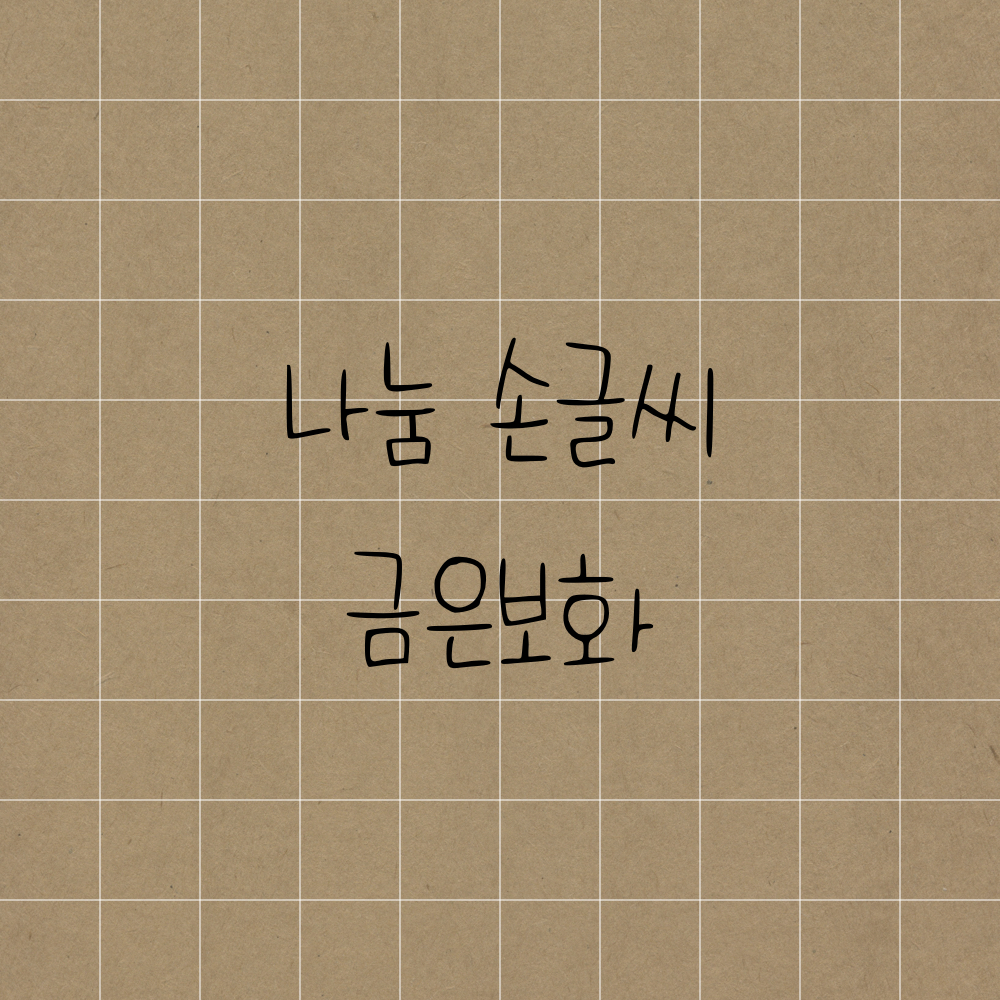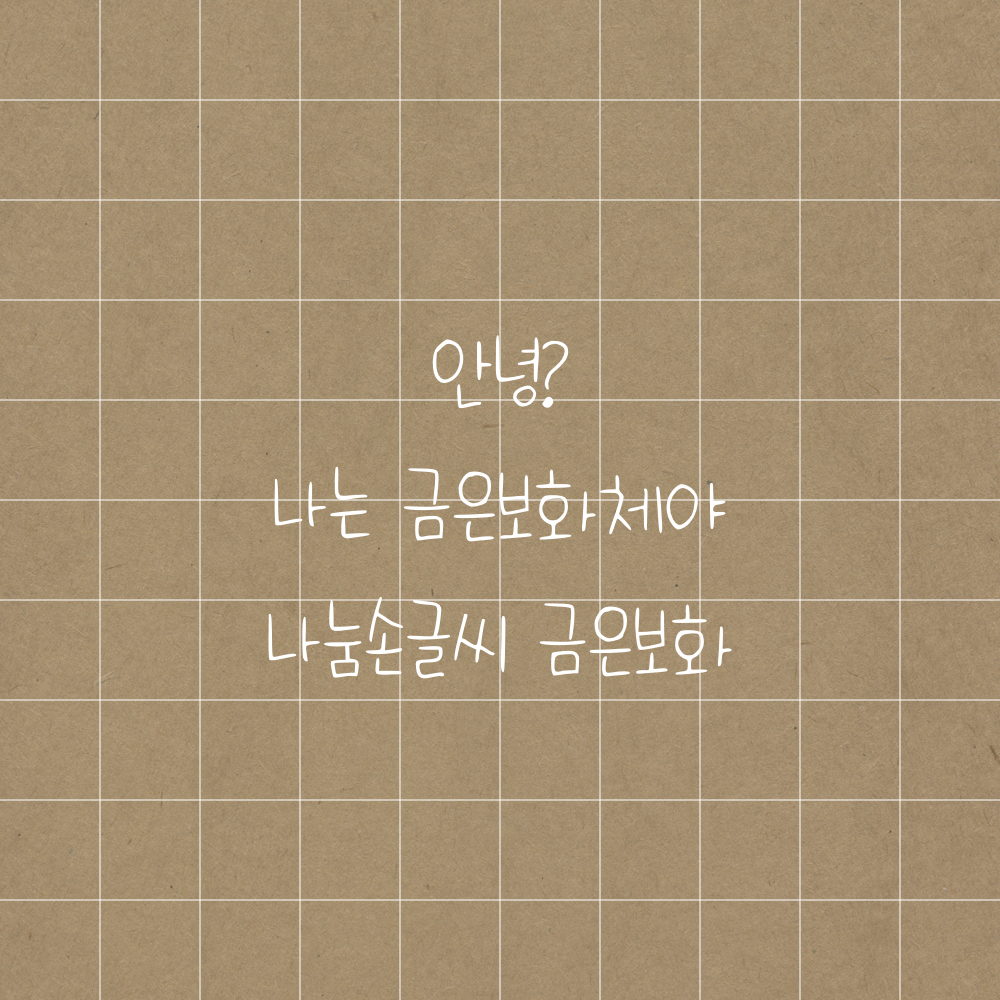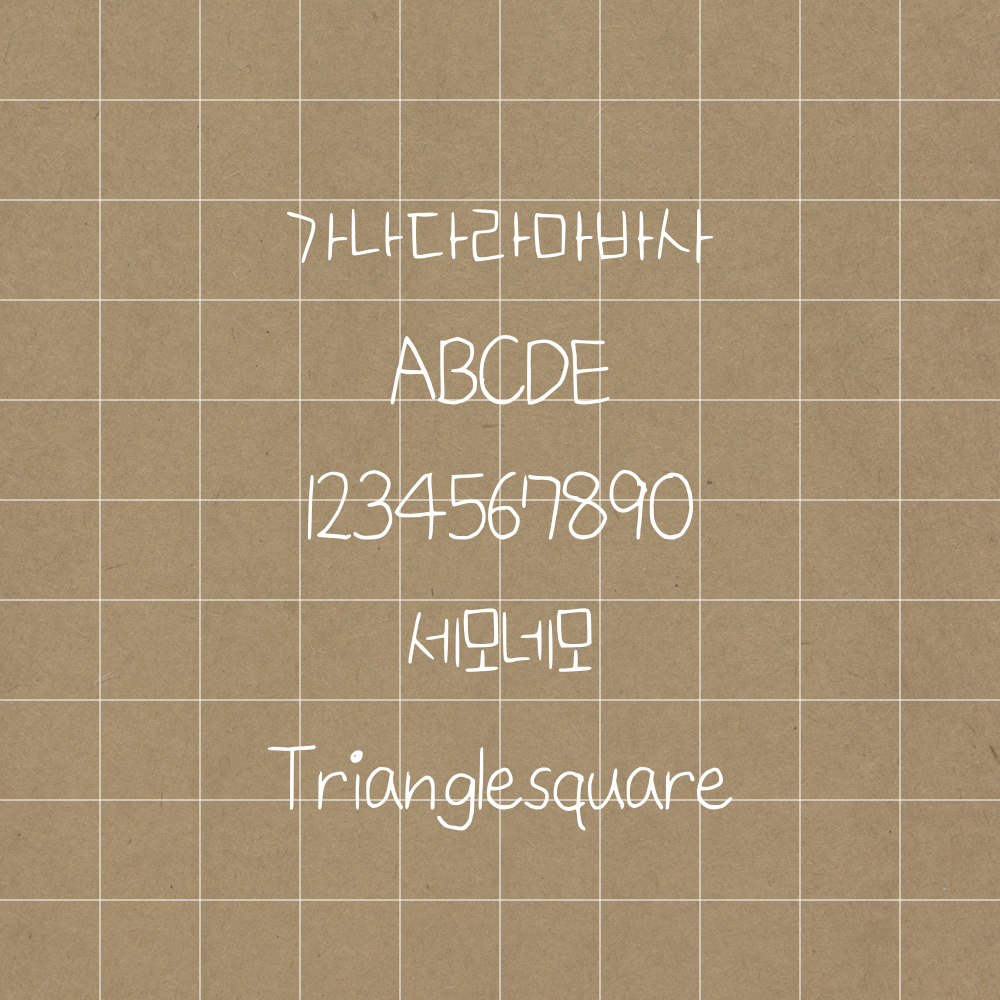
오늘의 폰트는 금은 보화체입니다⭐️ 원하는 대학에 합격하길 바라는 수험생이 만든 폰트입니다. 아기자기한 폰트 구경하러 가볼까요~??🤓
금은보화체 알아보기😉
샘플을 살펴보겠습니다.😄
본인이 만든 폰트로 과제를 작성하고 싶다는 간절한 소망이 담긴 수험생의 인트로..
손글씨 폰트로 과제를 제출한 사람을 본적 없지만.. 비밀로 할게요..😘 합격길만 걷길🤓
다꾸하기에 적합한 아기자기 폰트니까 플래너로 대체하는건 어떨까요~? ㅎㅅㅎ